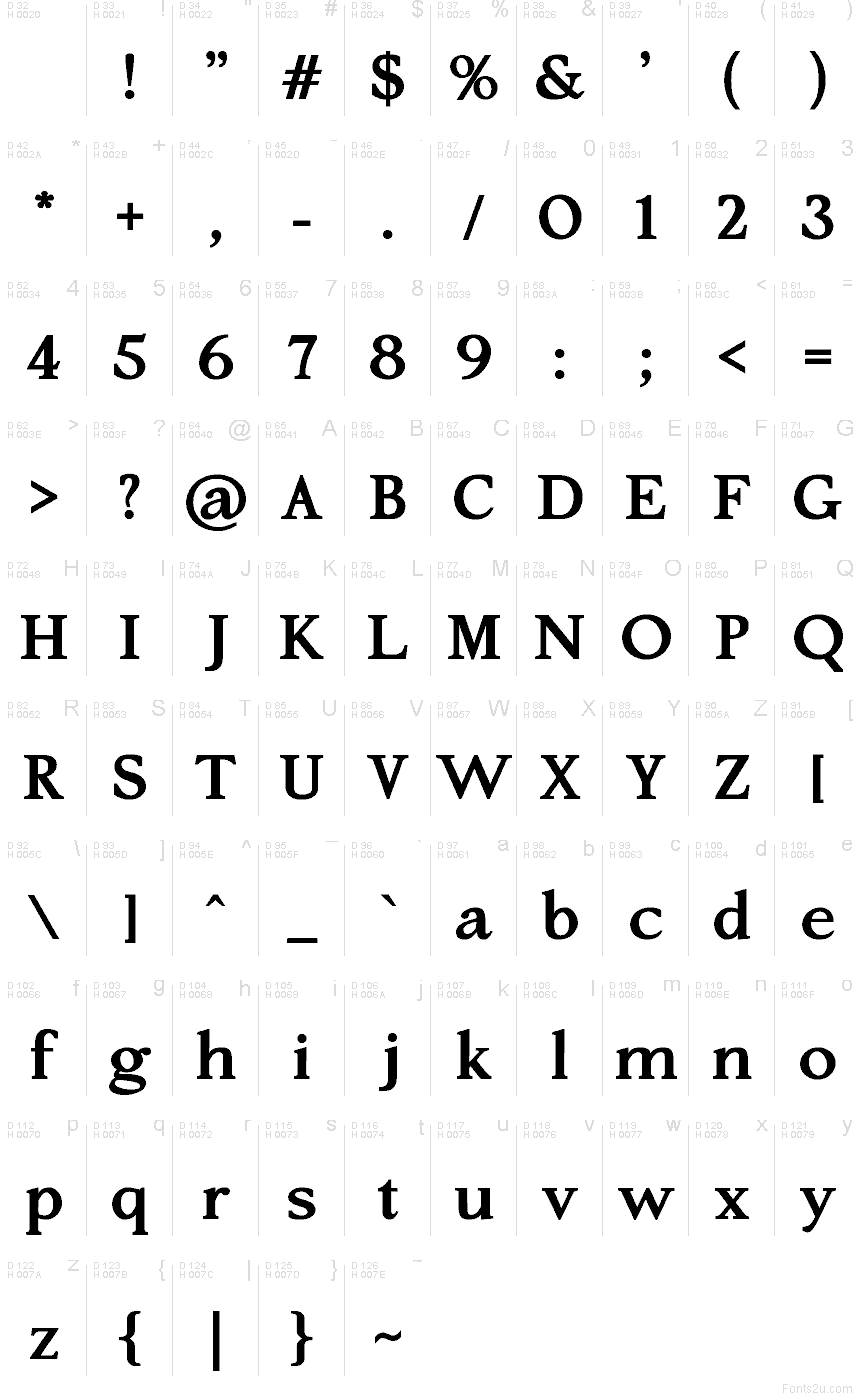
Silent Citadel Bold di Muhamad Fikry Nuralif del Fikryal Studio infonde una solida sicurezza letteraria nella famiglia Silent Citadel. Tratti spessi, spaziatura generosa e grazie nitide le conferiscono un aspetto scolpito: autorevole senza essere pretenzioso. È un carattere serif gratuito che rimane perfettamente leggibile anche quando viene ingrandito.
Silent Citadel Bold è ideale per titoli editoriali, copertine di libri, titoli per mostre o gallerie, packaging di alta gamma, locandine cinematografiche, loghi e citazioni. Accostalo a un font sans serif geometrico pulito per il testo principale e lascia che questo font gratuito prenda il centro della scena; un tocco di tracking extra mantiene il peso audace del carattere visivamente leggero.